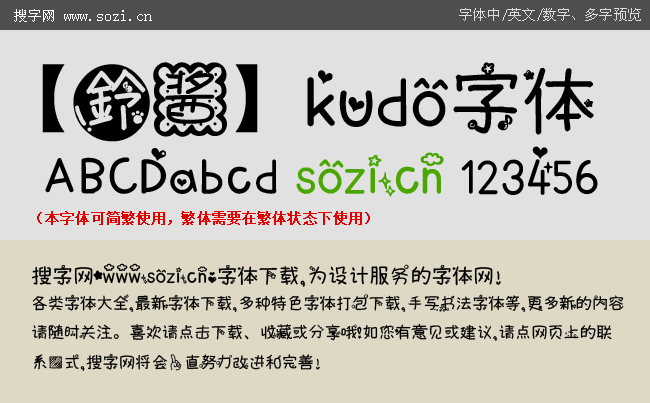
鈴醬萌系字體KUDO字體
搜字網(wǎng)給大家提供一款卡通手寫(xiě)風(fēng)格的手機(jī)中文字體下載。名字叫鈴醬萌系字體KUDO字體,這款手機(jī)字體是仿照兒童手寫(xiě)風(fēng)格的卡通手寫(xiě)字體,結(jié)構(gòu)帶有POP字體風(fēng)格,字體間還插入有趣的卡通圖案,特別適合喜歡手機(jī)字體個(gè)性一些的朋友在手機(jī)上安裝使用。